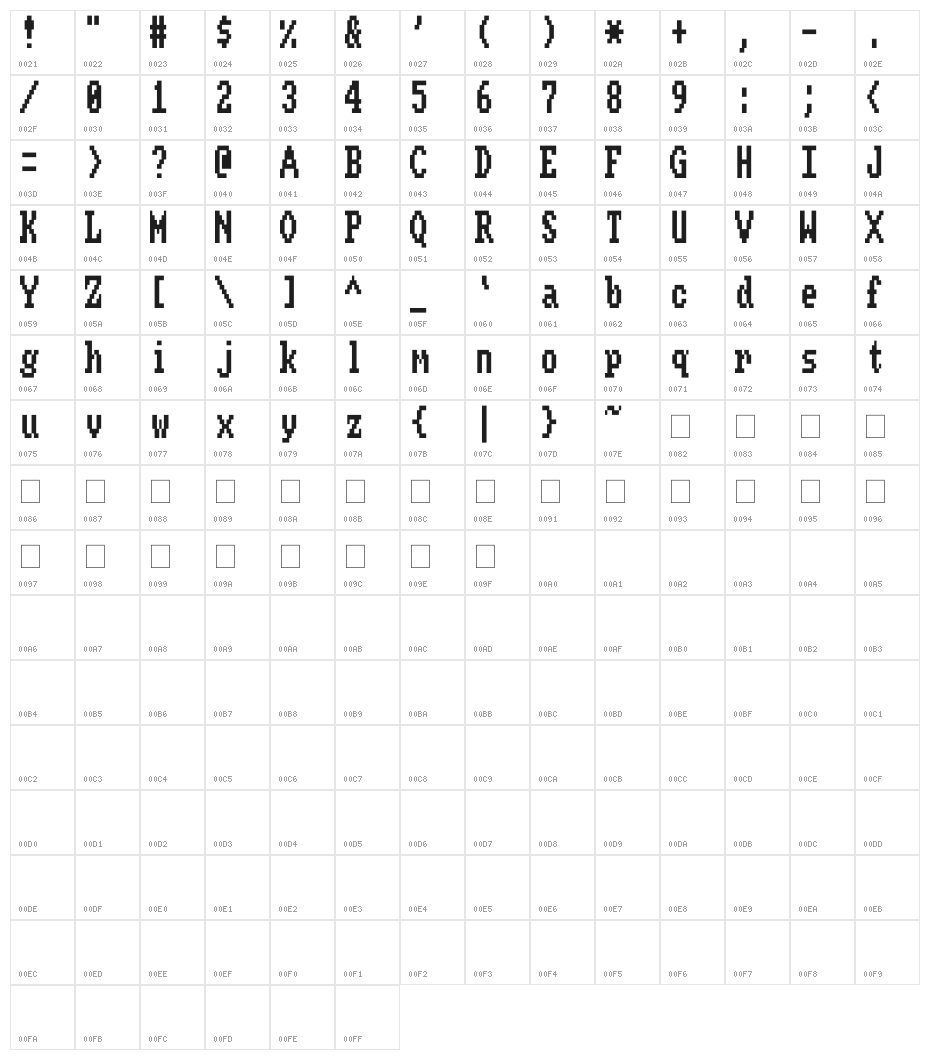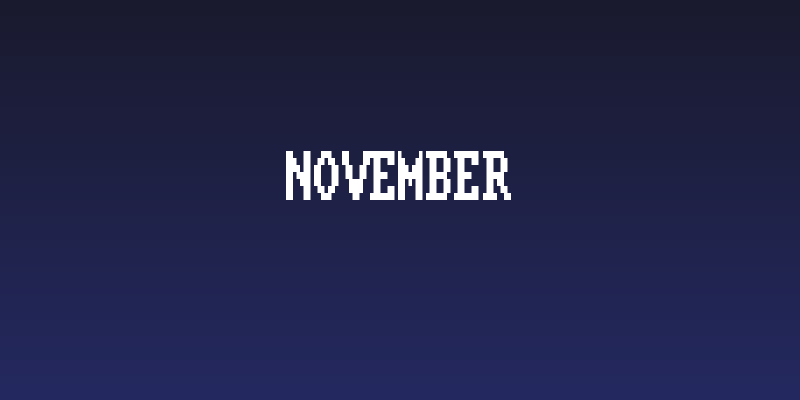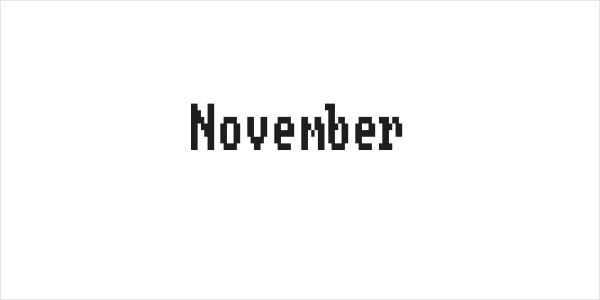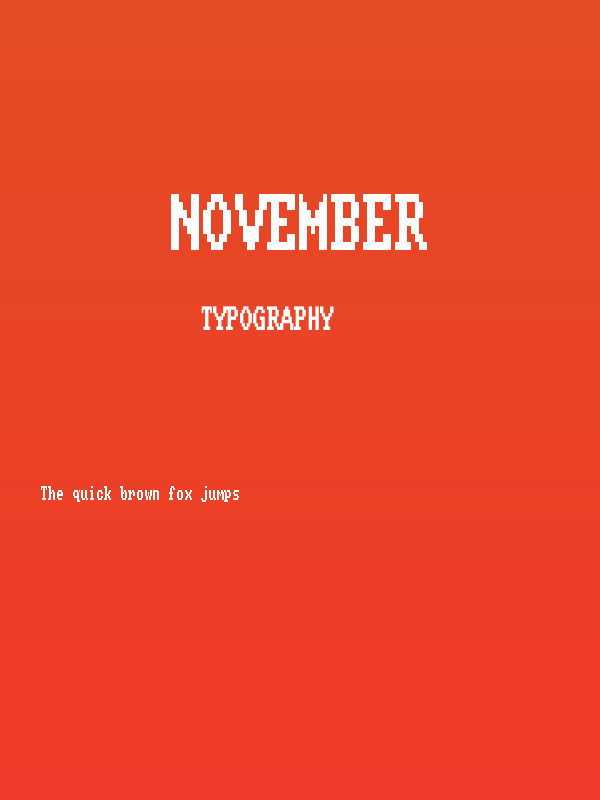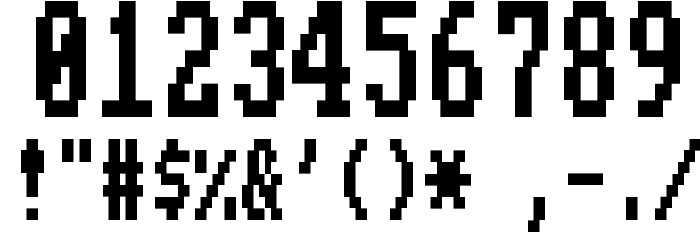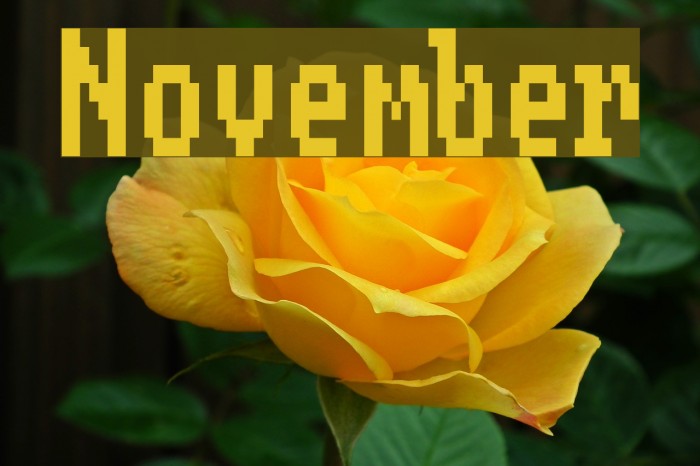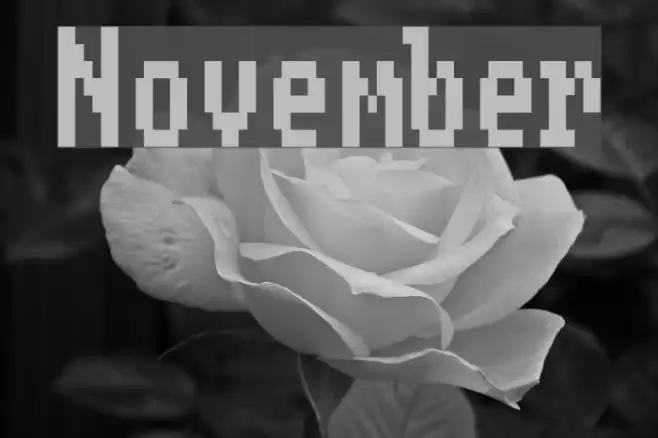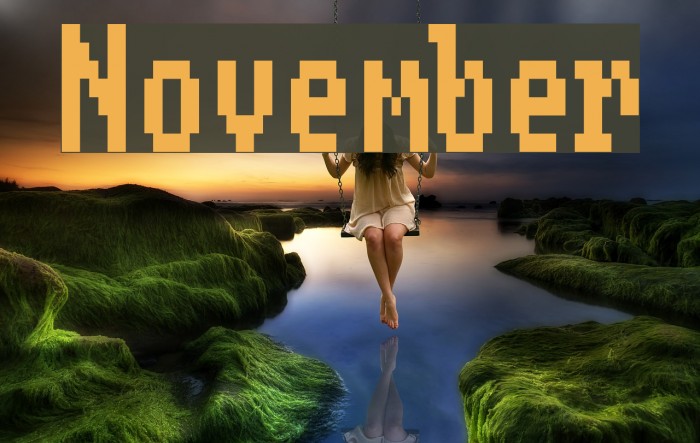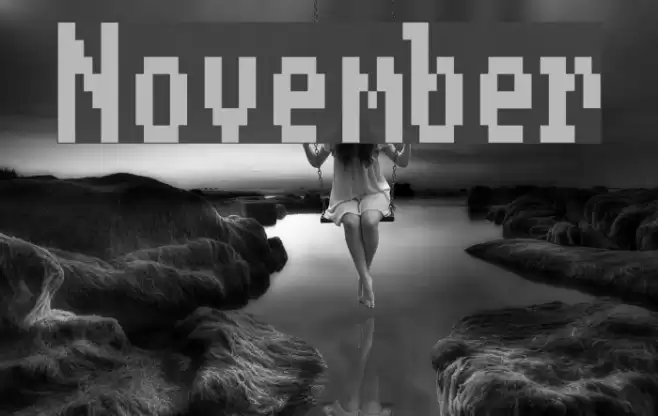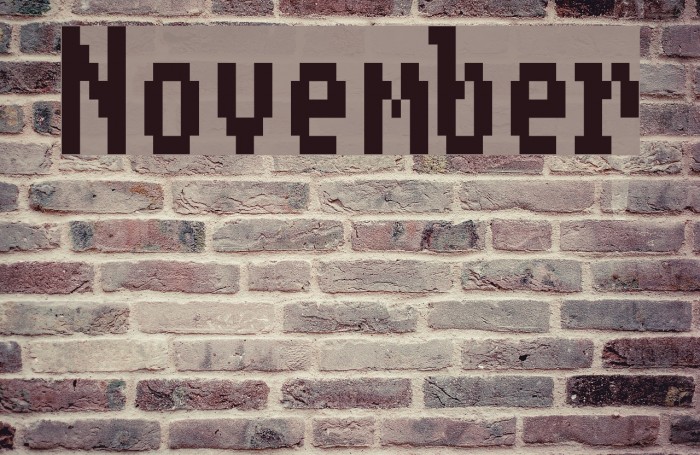
November Font
| Projetos propostos | Ideal for retro video game designs, digital art projects, tech-themed posters, and any creative work that seeks a nostalgic digital aesthetic. |